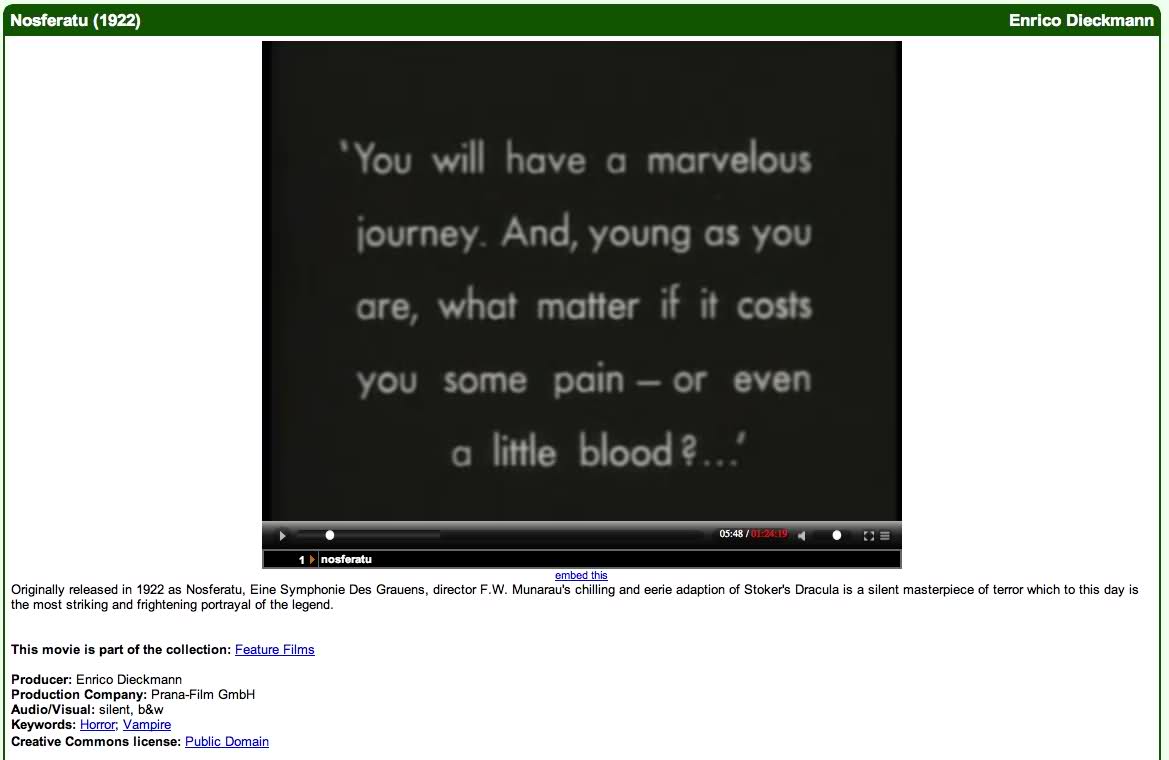
Nosferatu - Futura?
Hallo, beim Stöbern auf Spiegel bin ich auf http://www.archive.org/details/nosferatu_ipod mit Nosferatu und den Texttafeln gestoßen.
Die Schriftart ist doch die Futura, oder?
Der Film von 1922. Die Futura laut Wikipedia erst von 1927. Wo ist mein Denkfehler? Wahrscheinlich wurde die englische Fassung erst später erstellt. Oder ist das etwa nicht die Futura? :tutor:
gab es nicht ein paar Vorläufer-Versionen von der Futura? Renner hat doch lange dran gestrickt. Oder der Vorspann ist nachträglich angefügt worden.
Die Futura ist es wohl.
Vielleicht wollte Renner auch den Film fördern und hat schonmal eine Version spendiert?
Soweit ich weiß, fing Paul Renner um 1924 mit den ersten Studien und Skizzen zur Futura an. Eine Vorversion kann es also nicht gewesen sein.
Von daher liegt die Vermutung nahe, dass der Vorspann später hinzugefügt wurde.
Dieser Screenshot stammt ziemlich sicher nicht vom Orginal aus 1922. Dafür ist die Qualität einfach zu gut. Im Wikipedia steht: "Am 29. Dezember 1988 wurde eine restaurierte und mit Musik von Hans Posegga neu vertonte Fassung des Films im ZDF erstaufgeführt, die auch die ursprünglichen Farb-Viragen wieder herstellte.".
Das dürfte auch die Antwort sein.
Die Futura scheint wohl das Werk der Restaurateure (BFI) zu sein, denn in Murnaus eigtl. Fassung hatten die Zwischentitel wohl eher den Anschein "realer" (und damit handgemachter) Dokumente - scheint ja damals nicht unüblich gewesen zu sein, wie man hier sehen kann: